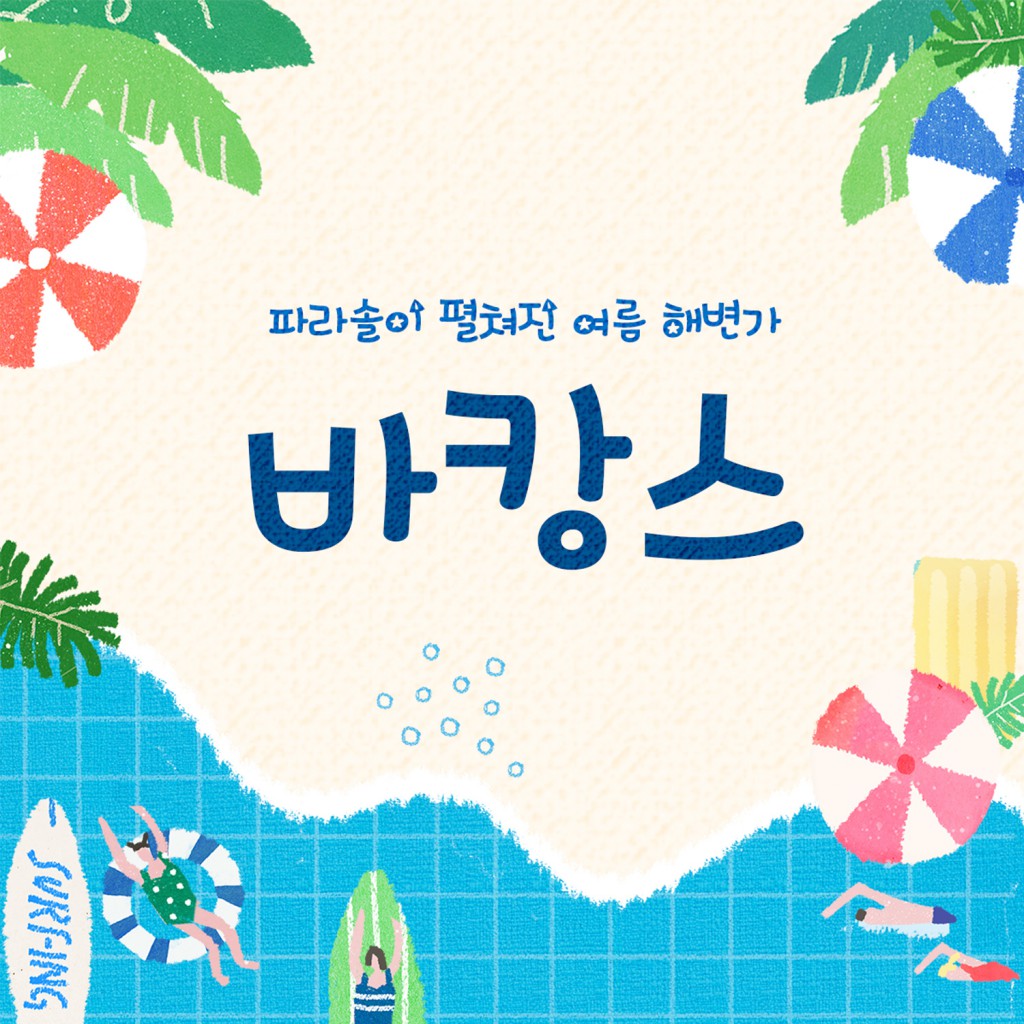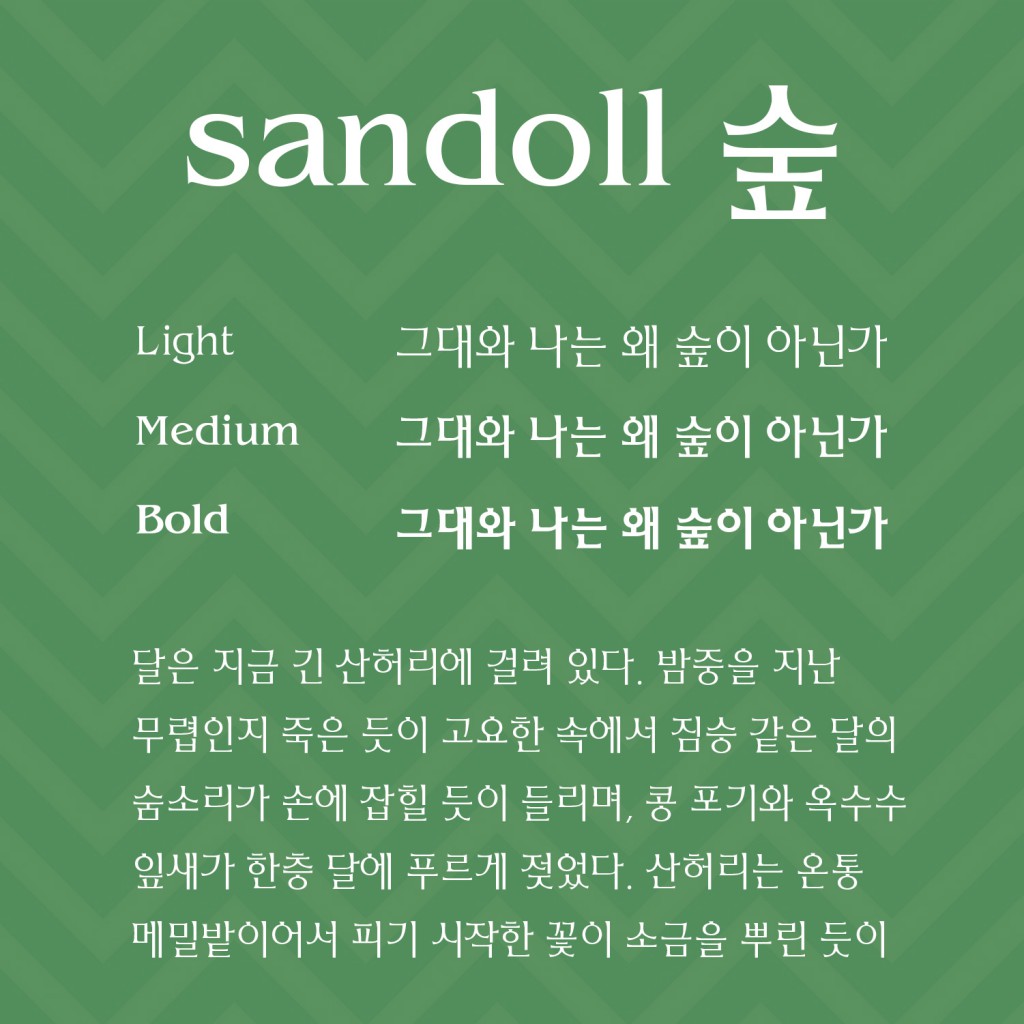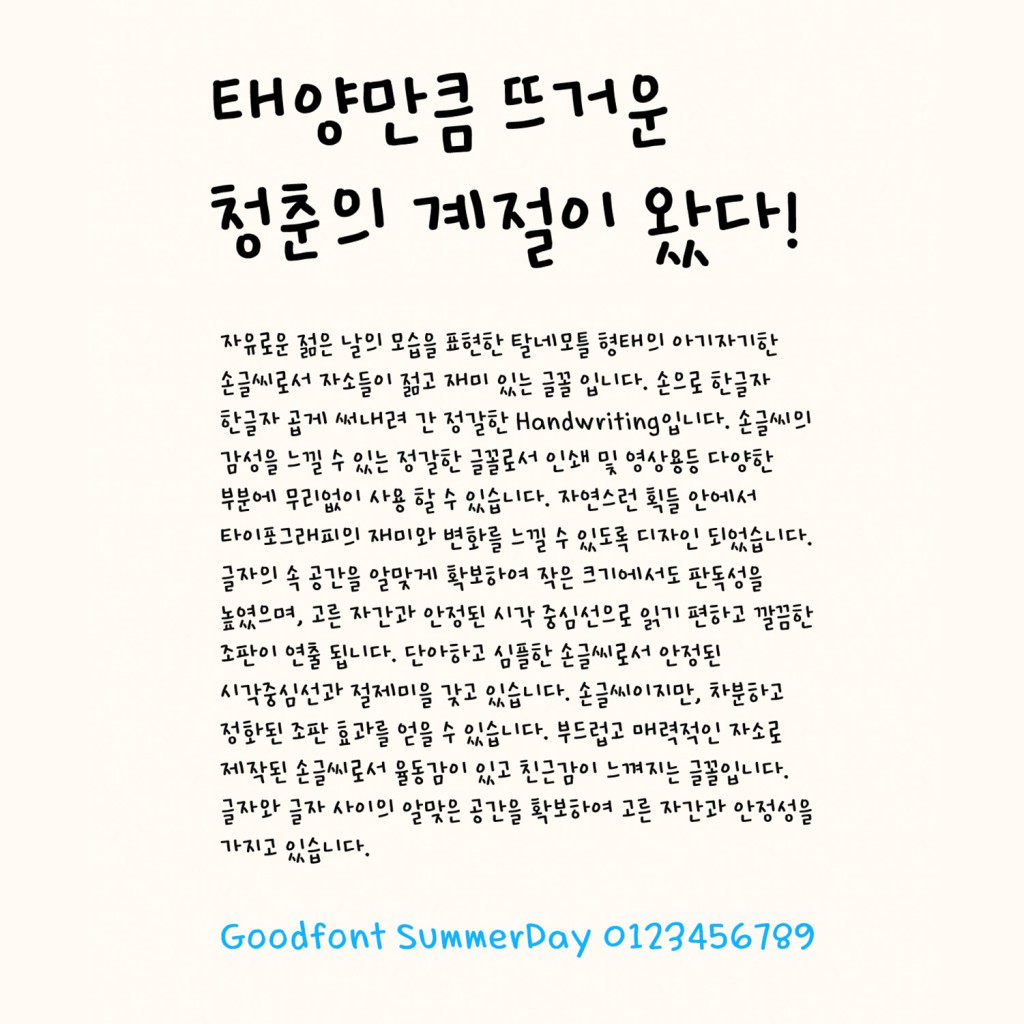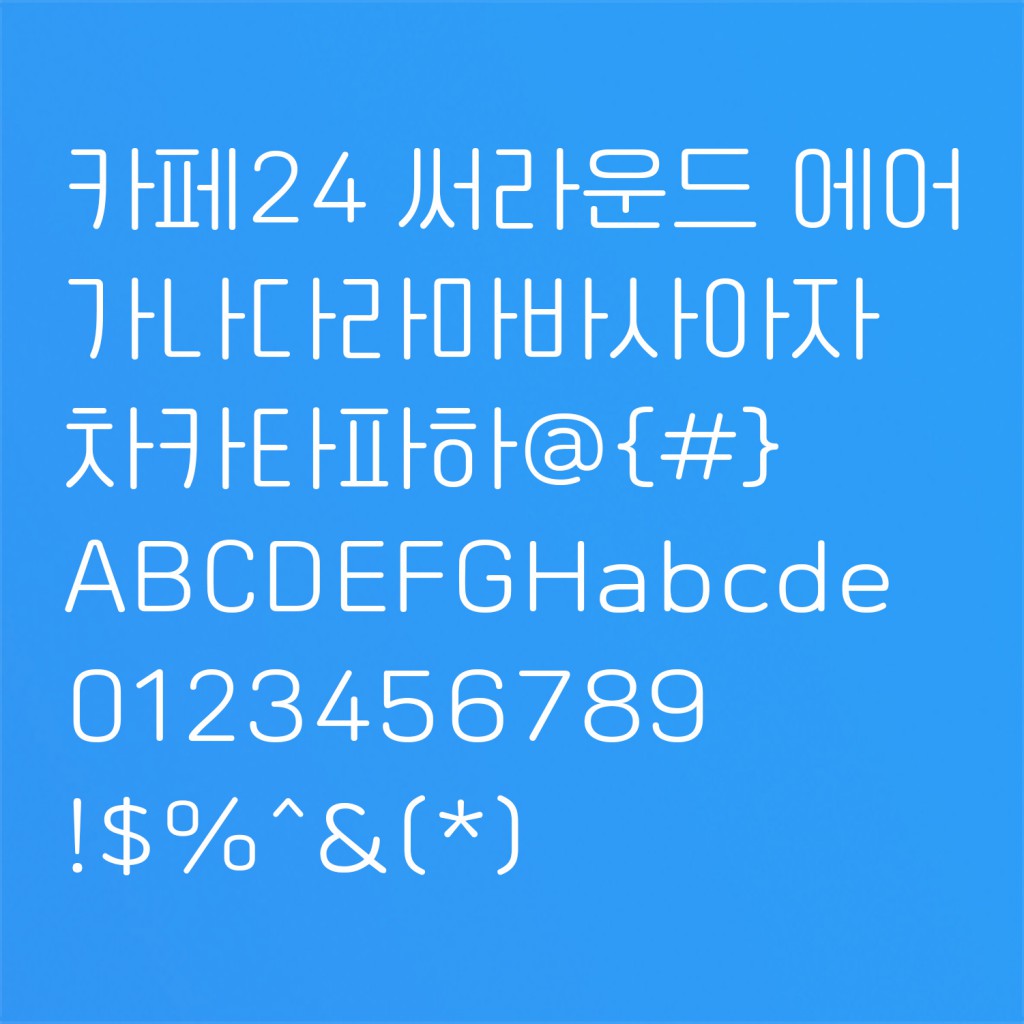
8월의 추천 폰트
폰트에는 정답이 없어요. 어떤 폰트를 어디에 사용하느냐에 따라서 그 결과가 천차만별이거든요. 그래서 작업에 어울리는 폰트를 찾기 위해 이 폰트, 저 폰트 작업에 얹어가며 비교하기도 하고, 때로는 찾을 땐 없다가도 “이런 폰트가 있었어?”라고 할 정도로 숨어있는 폰트들이 갑자기 보일 때도 있죠.
오늘은 여름의 달 8월을 맞이해 보기만 해도 시원하고 청량감 넘치는 폰트 5개를 선별해 보았어요. 남들 다 쓰는 폰트는 지겹고, 그렇다고 딱히 뭘 써야할 지 모르겠을 때에는 아래 소개된 폰트들을 한 번 활용해보세요 👍
카페24 써라운드 에어 TTF
역시 여름 콘텐츠에는 얇은 제목용 폰트가 빠질 수 없겠죠? 넓은 속공간과 얇은 두께로 인해 시원시원한 인상이 특징인 ‘카페24 써라운드 에어’를 소개합니다. 웹사이트 콘텐츠의 헤드라인으로 사용하면 깔끔하면서도 예쁜 표현이 가능해져요. 아, 그리고 카페24 써라운드 에어는 무료폰트예요. 누구나 사용할 수 있고, 어디에든 사용할 수 있죠. 산돌구름을 사용하시는 분들이라면 구름다리의 무료폰트 카테고리에도 들어있으니 굳이 다운받지 않더라도 편하게 사용하실 수 있습니다.
Sandoll 숲
‘Sandoll 숲’은 우아한 곡선의 돌기가 특징인 폰트예요. ‘숲’이라는 이름처럼 조판된 걸 보고 있노라면 마치 전나무숲을 보는 듯한 아름다움을 느낄 수 있죠. 획도 시원스레 쭉쭉 뻗어 있고, 회색도도 낮아 답답한 느낌도 없고요. 장식적이면서도 낭만적인 이미지를 연출할 수 있어 리플렛이나 안내장에 사용하면 시원하면서도 고급스러운 느낌을 표현할 수 있을거예요.
GF왔다썸머
탈네모꼴의 폰트를 사용하면 글줄 자체에서 리듬감이 느껴지기 때문에 텍스트에 흥이 돋아납니다. ‘GF왔다썸머’도 탈네모꼴 폰트로서 이런 리듬감을 주기 제격인 폰트죠. 손글씨의 형태를 따른 자유로운 형태의 자소들이 감성적이면서도 시원한 분위기를 연출합니다. 11,172자 모두 지원하며 인쇄물, 출판, 영상 등 장르를 가리지 않고 다양한 영역에서 활용할 수 있다는 장점도 있어요.
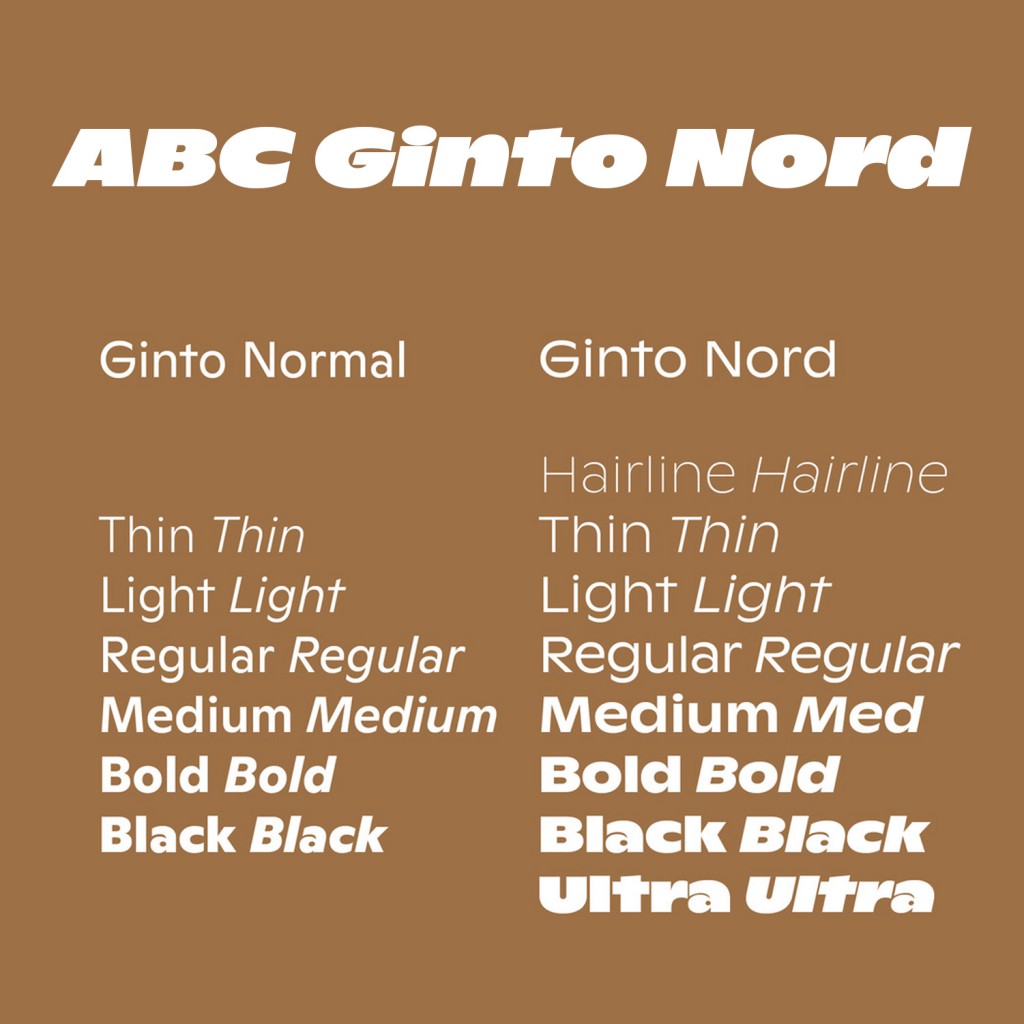
ABC Ginto Nord
디나모는 그래픽 디자이너들이 정말 좋아하는 타입 스튜디오예요. 영문 폰트지만 재미있는 폰트들이 정말 많죠. ‘ABC Ginto Nord’도 강력하게 시선을 잡아 끄는 폰트 중 하나인데요. Hairline부터 Ultra까지 극명한 두께의 차이를 보세요. 저렇게 강약의 대비가 큰 폰트들로 콘텐츠를 꾸민다면 시원시원하면서도 힘있는, 더위를 확 날려버릴 것만 같은 디자인이 가능하지 않을까요?! 특히 저는 Ultra에서의 ‘r’과 ‘a’가 너무 맘에 든답니다.
Sandoll 바캉스
제목만 봐도 딱 아시겠죠? 휴가철에 정말 잘 어울리는 폰트, 바로 ‘Sandoll 바캉스’입니다. “이런 펜시한 느낌의 폰트를 요새 누가 써?”라고 생각하신다면 그건 크나큰 오산! 자소에 파라솔 모양, 불가사리 모양이 붙어 있어 SNS와 같이 가벼운 게시물이나 여름용 시즌성 콘텐츠, 영상의 상황 자막 같은 곳에 사용하면 개성과 여름느낌을 동시에 연출할 수 있을 거예요!